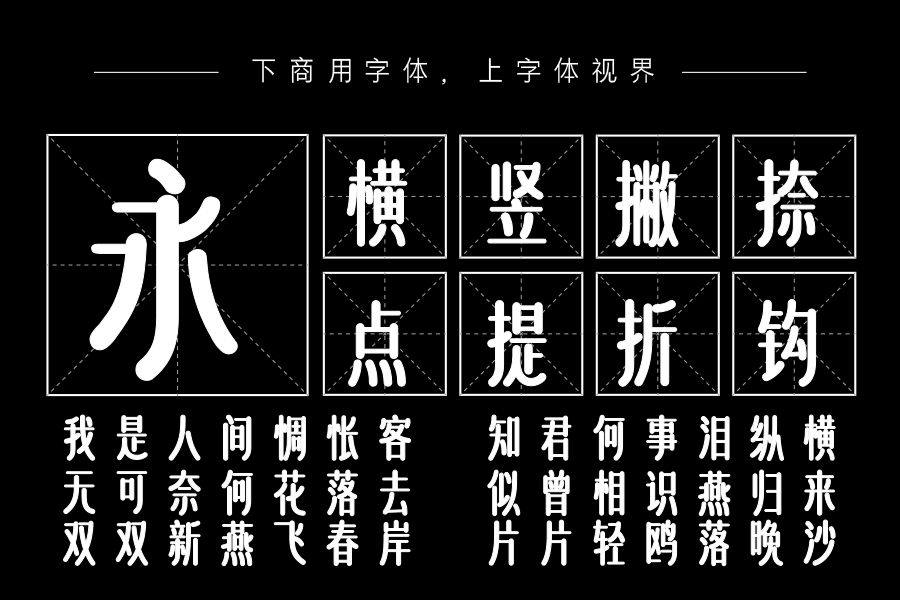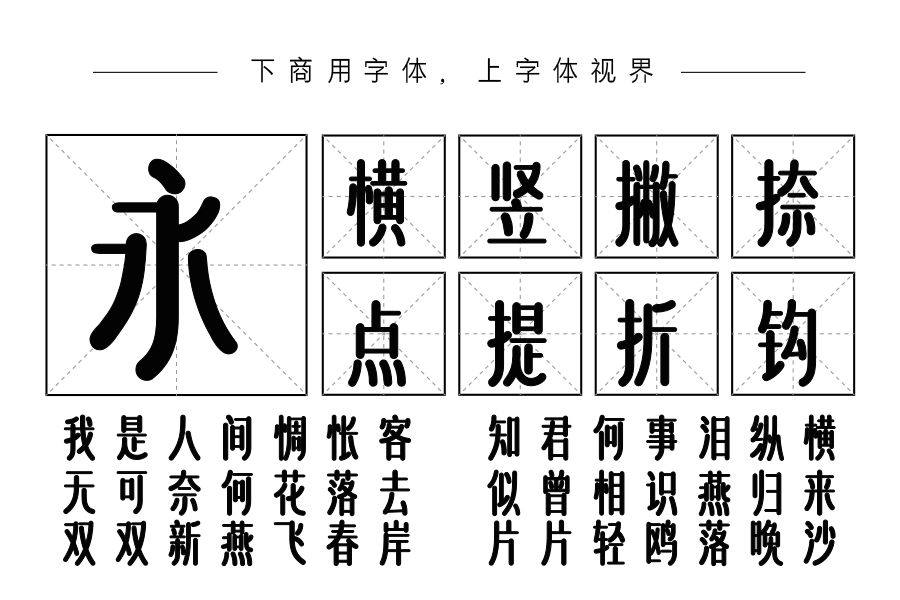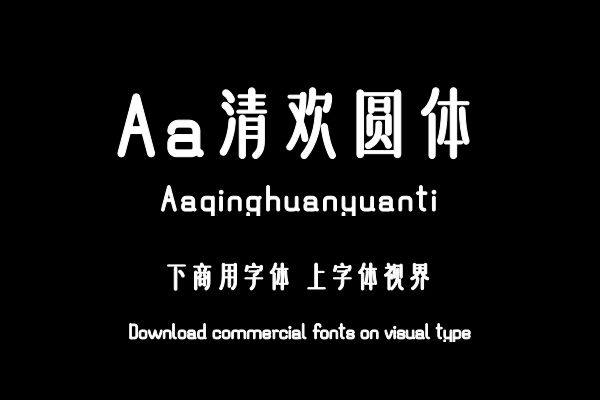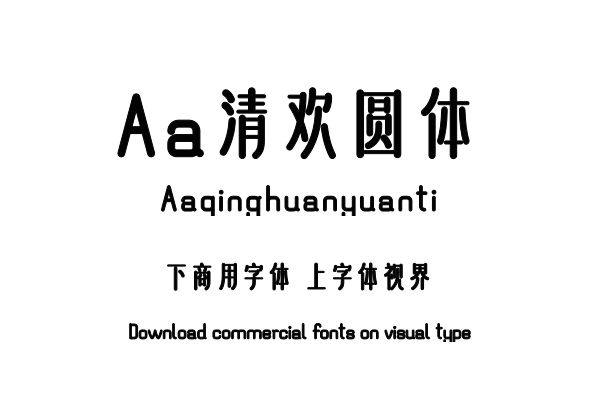
一款横细竖粗的标题圆体,拉长的字形和垂顺的竖笔画给字体带来优雅的视觉感受,粗竖笔画的圆头又平添一份优雅童趣的气质。购买须知:“下载服务费”与“字体VIP”所获得字体 仅用于个人非商用, 商用请联系付费授权。本字体为电脑用字,手机没有root权限不支持直接手机换字(手机如何root,请自行百度搜索教程)。购买前请先 了解清楚后再付款 ,字体为虚拟产品无法回收 一旦购买不支持退款。